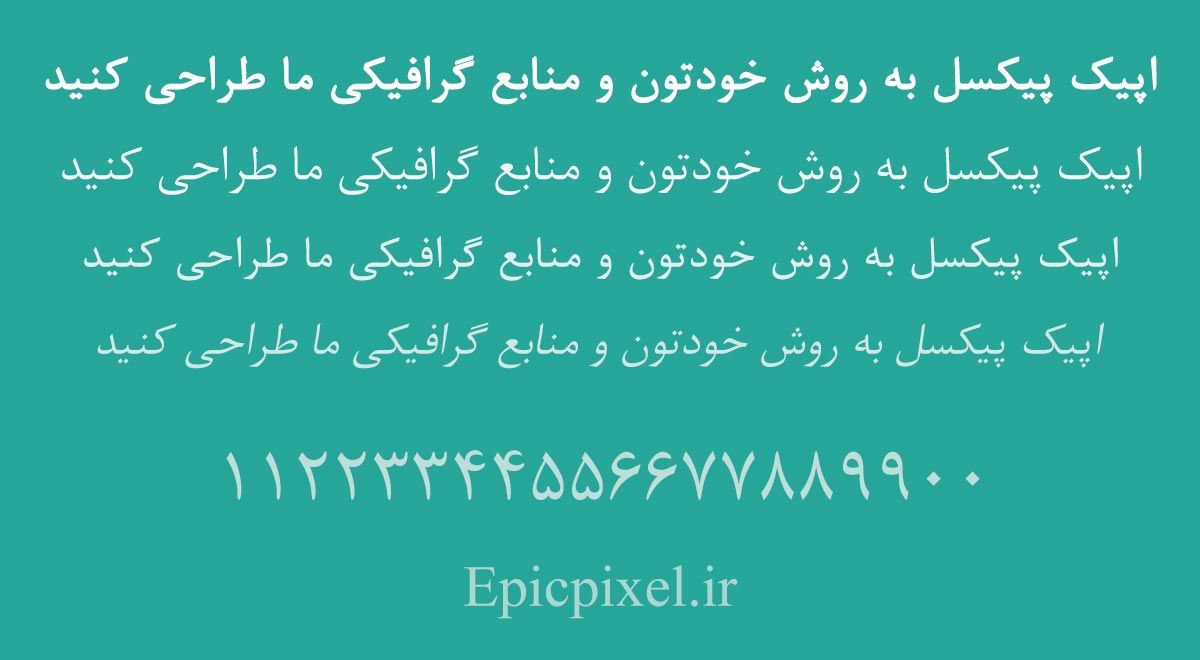
مجموعه فونت سری 2 فارسی (+86 فونت)
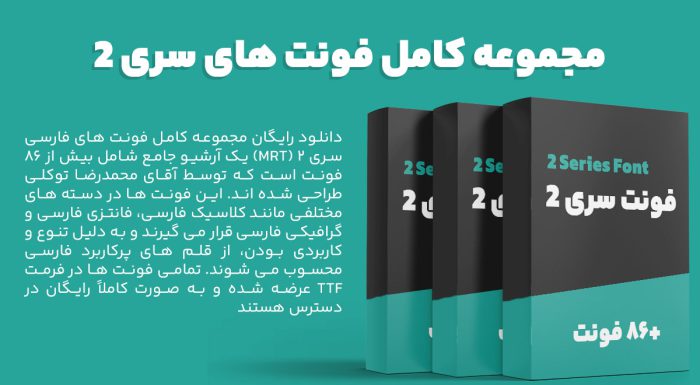
دانلود رایگان مجموعه کامل فونت های فارسی سری ۲ (MRT) یک آرشیو جامع شامل بیش از ۸۶ فونت است که توسط آقای محمدرضا توکلی طراحی شده اند. این فونت ها در دسته های مختلفی مانند کلاسیک فارسی، فانتزی فارسی و گرافیکی فارسی قرار می گیرند و به دلیل تنوع و کاربردی بودن، از قلم های پرکاربرد فارسی محسوب می شوند. تمامی فونت ها در فرمت TTF عرضه شده و به صورت کاملاً رایگان در دسترس هستند، که آن ها را برای طراحان وب سایت و گرافیست های خلاق برای استفاده در انواع پروژه های تبلیغاتی و تجاری، ابزاری ایده آل می سازد. این مجموعه مورد تأیید گرافیست های برجسته نیز هست.
مجموعه کامل فونت سری ۲ فارسی MRT: بیش از ۸۶ قلم کاربردی و رایگان
فونت های سری MRT (که مخفف نام طراح آن، محمدرضا توکلی است)، یک مجموعه کامل و بی نظیر از قلم های فارسی هستند که به مرور زمان به تعداد آن ها افزوده شده و اکنون شامل بیش از ۸۶ فونت متنوع می باشند. این مجموعه با هدف ارائه ابزارهای کارآمد و زیبا برای طراحان گرافیک و وب، توسعه یافته است.
از ویژگی های کلیدی این مجموعه فونت می توان به موارد زیر اشاره کرد:
- تنوع در دسته بندی: فونت های سری MRT در دسته بندی های پرکاربرد و مختلفی از جمله کلاسیک فارسی، فانتزی فارسی و گرافیکی فارسی قرار می گیرند. این تنوع مدل ها به طراحان امکان می دهد تا برای نیازهای گوناگون پروژه های خود، از عناوین و تیترها تا متون با جزئیات خاص، گزینه های متعددی در اختیار داشته باشند.
- کیفیت بالا و تست شده: این مجموعه فونت ها کاملاً سالم و تست شده بوده و از کیفیت بالایی برخوردار هستند، که این امر اطمینان خاطر را برای استفاده در پروژه های حرفه ای فراهم می آورد.
- پشتیبانی کامل از زبان فارسی: تمامی فونت ها دارای حروف و اعداد فارسی هستند که امکان تایپ کامل و صحیح متون فارسی را فراهم می آورد.
- پرکاربرد و مورد تأیید: فونت های این مجموعه از قلم های پرکاربرد فارسی محسوب می شوند و مورد تأیید گرافیست های حرفه ای نیز هستند. این مجموعه با هدف صرفه جویی در وقت طراحان برای پیدا کردن فونت های خوب و زیبا تهیه شده است.
این مجموعه شامل فونت هایی با سبک های متنوع مانند:
دانلود- فونت های کلاسیک و رسمی: مانند فونت های باران، بدر، کامران، میترا، نازنین و رویا با وزن های مختلف (رگولار، بولد، ایتالیک).
- فونت های فانتزی و خاص: مانند فونت های فانتزی، بچه دزد، کودک و نیکی با جلوه های ویژه (اوت لاین، شدو، حاشیه دار).
- فونت های گرافیکی و مدرن: مانند فونت های آسمان، بردیا، مشهد، تیتر و ترافیک با استایل های گوناگون.
کاربردها: توسعه بصری در پلتفرم های مختلف
فونت های فارسی سری ۲ (MRT) با تنوع و قابلیت های گسترده خود، برای طیف وسیعی از کاربردها در محیط های چاپی و دیجیتال مناسب هستند:
- طراحی گرافیکی و تبلیغات:
- مناسب برای طراحی انواع پروژه های تبلیغاتی و تجاری از جمله طراحی پوستر، طراحی کارت ویزیت، طراحی تراکت و طراحی بنر.
- ایده آل برای طراحی کاورهای اینستاگرامی و سایر محتواهای بصری برای شبکه های اجتماعی.
- کارآمد برای عنوان نویسی و تیترها در طراحی های چاپی و دیجیتالی.
- طراحی وب سایت و اپلیکیشن: طراحان وب سایت می توانند از این مجموعه فونت های زیبا و خوانا برای بهبود تجربه کاربری و جلوه بصری وب سایت ها و اپلیکیشن ها بهره ببرند.
- نشر و مطبوعات: قابل استفاده در مجلات، روزنامه ها و کتاب ها برای متون اصلی و عناوین.